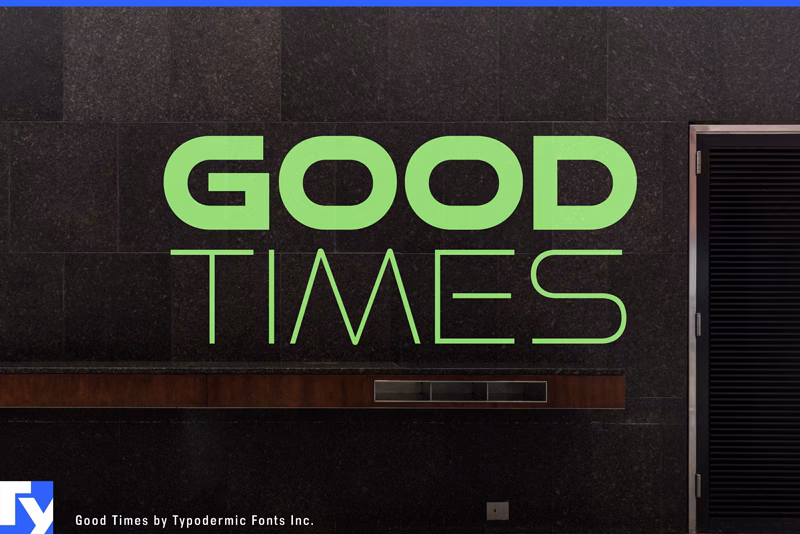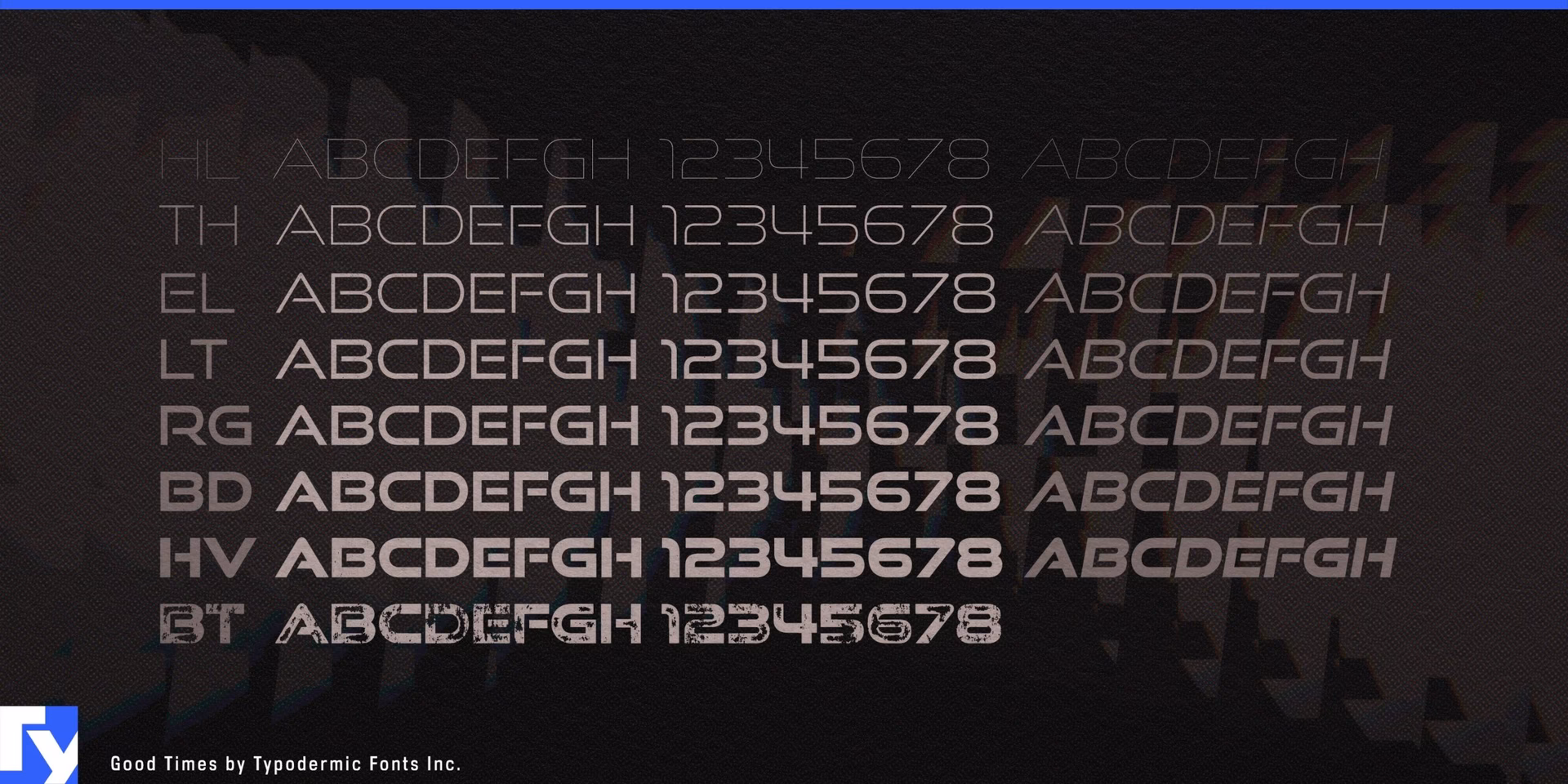
Good Times Skrifttypen: En Tidsmaskine til 90'ernes Techno-Futurisme
I en verden domineret af digitale grænseflader og konstant innovation, er der noget særligt ved skrifttyper, der kan transportere os tilbage i tiden. Good Times skrifttypen er netop sådan en skrifttype. Skabt i 1998 og senere overhalet, indfanger den essensen af 90'ernes techno-futurisme, inspireret af de højteknologiske bogstaver, der prydede Pontiac biler mellem 1989 og 1994. Good Times er ikke bare en samling af bogstaver; det er en typografisk revolution, der bringer en unik æstetik til dine designprojekter.
Hvad er Good Times Skrifttypen?
Good Times er en skrifttype, der emmer af fremtidsorienteret design, men med rødder solidt plantet i 90'ernes æstetik. Dens karakteristiske brede, kapselformede bogstaver er konstrueret med enkle, lige linjer, der minder om skæringen af højteknologisk udstyr og højtydende maskiner. Det er som om hvert bogstav er præcisionsskåret fra kølerhjelmen på en konceptbil, klar til at give dine designs et energifyldt boost.
Hvad er Nyt i Good Times Skrifttypen?
Siden dens oprindelige skabelse i 1998 har Good Times skrifttypen gennemgået betydelige opdateringer. Disse opdateringer har udvidet dens funktionalitet og æstetiske appel:
- Udvidet Sprogunderstøttelse: Accenter dækker nu flere sprog, hvilket gør skrifttypen mere alsidig for internationale projekter.
- Nye Tegn: Good Times inkluderer nu brøker og numeriske ordinaler, hvilket øger dens anvendelighed i datapræsentationer og teknisk dokumentation.
- OpenType Funktioner: Når Good Times bruges i et OpenType-kompatibelt program, kan almindelige bogstavpar automatisk erstattes med specialdesignede par. Dette skaber en mere realistisk, stemplet effekt, der tilføjer karakter og dybde til dine designs.
Good Times Bad Times Variant: Tilføj Grit og Attitude
For dem, der søger et endnu mere markant udtryk, tilbyder Good Times skrifttypen en variant kaldet Good Times Bad Times. Denne version tilføjer en rusten tekstur, der forstærker den industrielle og "slidte" æstetik. Ved at aktivere OpenType-funktionerne i denne variant kan du opleve, hvordan bogstavpar forvandles til slidte metalmesterværker, der giver dine designs en autentisk og rå følelse.
Good Times skrifttypen er designet med fokus på ydeevne og æstetik. Med syv forskellige vægte, inklusive elegante obliques, giver skrifttypen dig et bredt spektrum af visuel kraft. Fra den fineste vægt til den mest dristige, har du værktøjerne til at finjustere dit budskab for maksimal effekt. Det er som at have et typografisk pit-stop lige ved hånden, klar til at optimere dine designs til optimal ydeevne.